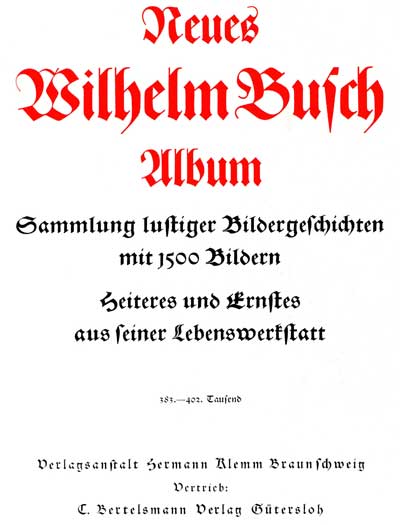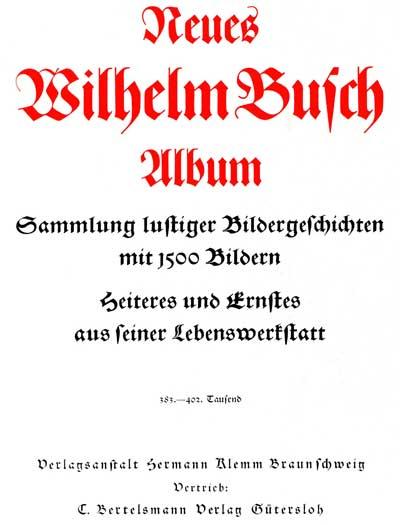
Schwabacher als Auszeichnungsschrift im Fraktursatz?
Ich lese hin und wieder, dass in Frakturtexten Schwabacher als Auszeichnungsschriften genutzt wurden, neben dem Sperrsatz und anderen Frakturen. Allerdings ist das einzige mir bekannte Beispiel hierfür ein alter norwegischer Text – und ich bilde mir ein, nicht wenig Frakturtexte gesichtet zu haben. Mir kommen deshalb so langsam Zweifel, zumindest was eine weitläufige Verwendung dieser Vorgehensweise angeht.
Kennt irgendjemand Beispiele, in denen Schwabacher zur Auszeichnung innerhalb von Fraktur genutzt wurde, oder weiß gar über die Geschichte dieser Praxis bescheid?
Als Auszeichnungsschrift im Sinne von „Kursiv für Fraktur“ habe ich das ehrlich gesagt aucxhg nie gesehen. Was ich dagegen recht häufig vorgefunden habe, ist eine Schwabacher als Schriftart für Überschriften.
Einen direkten Buchtitel kann ich jetzt nicht nennen, da die Bücher zumeist nicht lange in meinem Besitz waren, oder nur ausgeliehen.
Als Auszeichnungsschrift im Sinne von „Kursiv für Fraktur“ habe ich das ehrlich gesagt aucxhg nie gesehen. Was ich dagegen recht häufig vorgefunden habe, ist eine Schwabacher als Schriftart für Überschriften.
Einen direkten Buchtitel kann ich jetzt nicht nennen, da die Bücher zumeist nicht lange in meinem Besitz waren, oder nur ausgeliehen.
Danke, dann bin ich schon mal nicht alleine. Es geht mir übrigens genau den Fall Kursiv für Fraktur und nicht um Überschriften (dafür kenne ich auch einige Beispiele).
Ich persönlich kenne da mehr, dass man alles, was man heute kursiv setzen würde, in Fraktur durch Antiqua ersetzt hat. also nicht nur romanische Fremdworte und Namen.
Was ich jedoch von recht alten Drucken kenne, dass es mit Fraktur und Schwabacher eine ziemliche Zwiebel-Bouillabaisse gab.
Gesperrt ist hier dann eher das äquivalent zu fett, wenn es von der Schrift keinen fetten schnitt gab, während Antiqua dann im wahrsten Sinne des Wortes „italic“ ist
(das bringt mich  jetzt auf die Idee, so einen Font-Satz zu bauen, bei dem zu einer Fraktur-Druckschrift dann der fürs Betriebssystem fette Font durch größere Vor- und Nachbreiten gesperrt ist, und für die kursiven Schnitte dann eine in Strichstärken-Kontrast zur Frakturschrift gut passende Antiqua gesellt wird.)
Die Idee hatte ich auch schon, aber das birgt das Problem, dass es relevant wird, ob der virtuelle Fettsatz vor oder nach einem Leerzeichen aufhört. Außerdem verwalten ja viele Programme ihre Leerzeichen gerne selbst.
Bei Antiquas hätte man dann bei den meisten freien Schriften das Problem, dass der Schriftname durch die Lizenzen ziemlich aufgebläht wird, und sonst hat man eh Probleme. Wenn man natürlich selbst einen Haufen Antiquas erstellt hat, ist das einfacher.
Zumindest im Web ist die Sache ja einfach, etwa so. Der Code ist trivial:
Das ist mir schon klar, dass ich da nicht einfach irgendjemandes Antiqua in meine Font-Familie mitr aufnehmen kann, aber wenn ich die Frakturbuchstaben schon zeichne, kann ich das bei einer hierzu passenden Antiqua ja wohl auch hin bekommen…
Und das mit dem Sperrsatz funktioniert eigentlich problemlos, egal on mit eigenem Leerzeichen, oder einem unter Kontrolle der Anwendung, und ohne Auswirkung, ob man vor oder nach dem Leerzeichen zu sperren (fett) beginnt, denn am Leerzeichen ändere ich dann nichts.
Das ist mir schon klar
Mir war doch auch klar, dass dir das klar war. Aber es gibt doch noch die hunderttausend Mitleser, von denen fünf vielleicht noch nicht wissen, wie einfach das ist …
Ich habe neulich mehrere Plakate mit in Fraktur gesetzten Slogans gesehen, innerhalb derer auftretende Akronyme aber in Antiqua-Versalien gesetzt waren. Sicherlich eine pragmatische Lösung, aber wie verbreitet war das?
(das bringt mich  jetzt auf die Idee, so einen Font-Satz zu bauen, bei dem zu einer Fraktur-Druckschrift dann der fürs Betriebssystem fette Font durch größere Vor- und Nachbreiten gesperrt ist, und für die kursiven Schnitte dann eine in Strichstärken-Kontrast zur Frakturschrift gut passende Antiqua gesellt wird.)
Ich nehme an, die Idee schlummert noch ungestört in der Ideenkiste? :-?
Das mit den größeren Vor- und Nachbreiten, um so bei Fraktur eine künstliche Fettung zu verhindern, und statt dessen die Fraktur gesperrt zu setzen (auch mit den historischen Konventiionen entsprechendem Umgang mit Ligaturen, wobei bei Sperrung einige aufgelöst, andere [Zwangs-]Ligaturen erhalten, und eine zwar aufgelöst, aber nicht gesperrt wurde) habe ich schon so bei meinen Schriften umgesetzt. Die Sache mit Fraktur + Antiqua in einer Familie stehtr noch aus, wobei hier die Auszeichnung als Antiqua eine andere Qualität hätte, was logisch aber mit in Antiqua auch gern kursiv gesetzten Fremsworten passen würde.
Zur Geschichte kam mir gerade vor die Nase, dass Adelung dies in »Umständliches Lehrgebäude« Band 2 ausdrücklich empfiehlt:
»durch die im Fraktursatz gebräuchliche Auszeichnungsschrift der Schwabacher« … für »fremdsprachige Wörter«. In Killius, die Antiqua-Fraktur-Debatte um 1800.
Und eine Schwabacher wird auch tatsächlich als Auszeichnungsschrift für Wörter genutzt, die sich selbst repräsentieren, was stellenweise zu den oben angesprochenen Unterscheidungsschwierigkeiten führt. Aber das Beispiel, was ich suchte, ist es allemal. Danke.